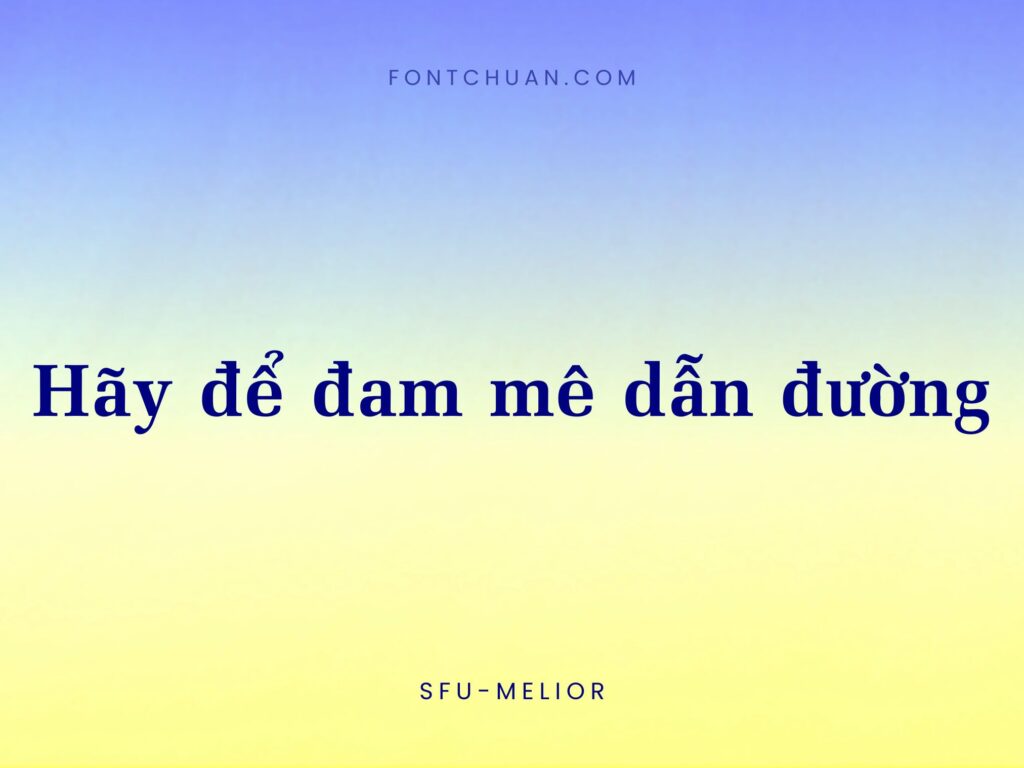
Melior là một kiểu chữ serif được thiết kế bởi Hermann Zapf và phát hành bởi xưởng đúc chữ Stempel vào năm 1952. Font này được sưu tầm và đăng bởi thành viên của Font Chuẩn. Melior nổi bật với thiết kế dựa trên hình siêu elip, tạo nên sự độc đáo và hiện đại, phù hợp cho nhiều mục đích sử dụng khác nhau. Với tính thẩm mỹ thanh lịch, Melior cũng là một lựa chọn lý tưởng để làm Font logo, mang lại sự chuyên nghiệp và phong cách cho các thương hiệu.
Về mặt thiết kế, Melior có các đường nét gọn gàng, tỷ lệ cân đối và độ tương phản cao, tạo cảm giác thanh lịch và chuyên nghiệp. Font này hỗ trợ nhiều ngôn ngữ và bao gồm các ký tự đặc biệt, giúp người dùng dễ dàng tùy chỉnh theo nhu cầu. Melior thường được sử dụng trong các thiết kế sách, tạp chí, nhận diện thương hiệu và các dự án cần sự trang trọng và chuyên nghiệp. Các ngành nghề như xuất bản, quảng cáo và thiết kế đồ họa có thể tận dụng kiểu chữ này để tạo dấu ấn đặc biệt trong truyền thông.